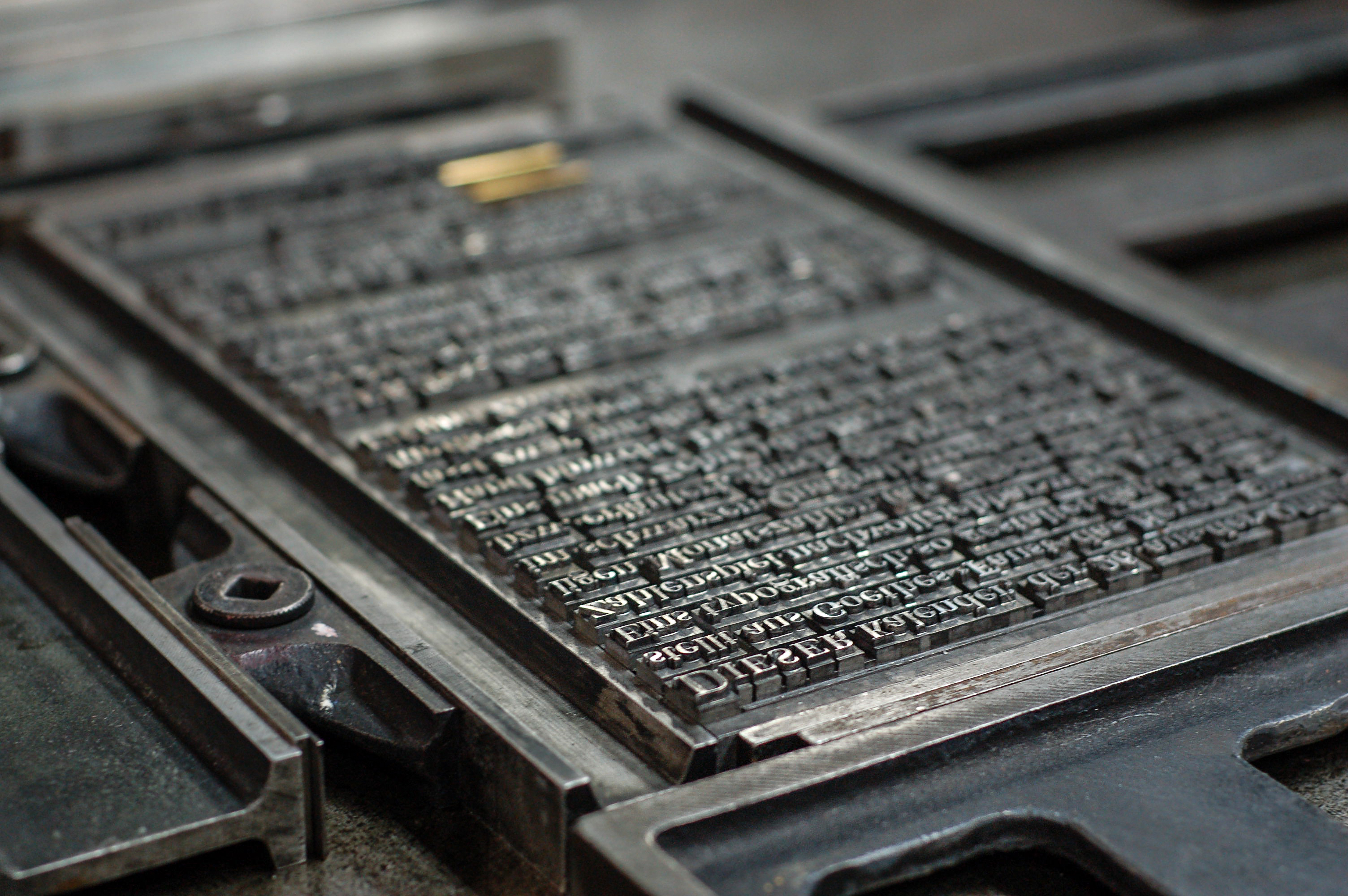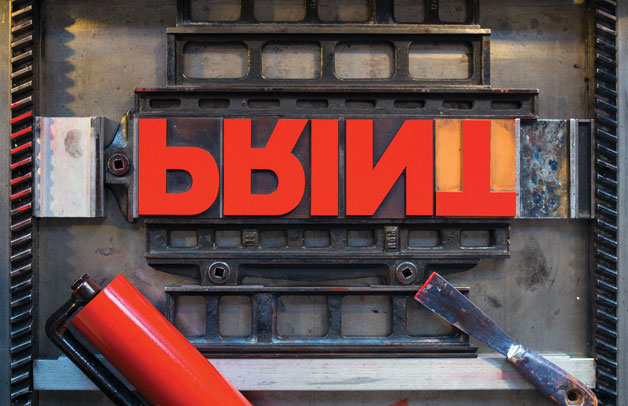
Ich suche ein Foto von Bleisatzlettern
Für einen Call for Content zum Thema «Maschinen» erstellen wir gerade Flyer und Plakate.
Ich hatte den Einfall, dass ein hochauflösendes Foto von einer Bleisatz-Druckmaschine, in die die Druckform mit dem Wort «Maschinen» eingesetzt ist möglicherweise ziemlich gut passen würde. (Das Foto würde ich vielleicht als Hintergrund des Plakats/Flyers benutzen. Wird aber schwarzweiss sein, nicht farbig.)
Ich weiss, dass einige von euch mit Bleisatz zu tun haben und wollte deshalb einfach mal ins Blaue fragen, ob jemand Lust und Zeit hat, ein solches Foto herzustellen und zur Verfügung zu stellen.
Ich weiss nicht, wie aufwendig es ist, so etwas zu fabrizieren mit Einsetzen und alles, verzeiht mir deshalb meine Unwissenheit, falls ich mit meiner Anfrage etwas Unanständiges verlange. :bow:
Ansonsten auch immer gerne Links zu Galerien posten, welche sich auf Fotos von Druckapparaturen, Schrift, Lettern, Typografie spezialisiert haben; würde mich auch sonst interessieren.
Ich schätze, Dir schwebt so was vor wie diese Beispielbilder bei Fotolia, oder? Dort wirst Du nur vermutlich Dein gewünschtes Wort nicht finden, das dürfte zu speziell sein. Falls Du aber doch fündig wirst: die Bildlizenzen bei Fotolia sind in der Regel nicht teuer.
Ansonsten könntest Du auch in eine offene Bleisatzwerkstatt gehen und Dir das Bild selber erarbeiten. Das geht zum Beispiel im Museum der Arbeit in Hamburg, immer montags.
Okay, jetzt hab ich’s verstanden. Das hatte ich gerade eben im Twitter-Stream:
Sowas, nicht war?
wow das gefällt sehr gut. wunderschön. Jap genau sowas schwebt mir vor :D
Ein paar Lettern in den Schließrahmen zu stellen, ist keine große Sache. Wenn du mir eine grobe Skizze machst, in welcher Perspektive und mit wieviel Fleisch drumherum das Bild sein soll, kann ich das machen. Ich fotografiere fast täglich in der Werkstatt. Langzeitbelichtung, kleine Blende, den Rest kannst du dann retuschieren. Welche Art Schrift? Mit oder ohne Serifen? Blei oder Holz?
Das Bild mit der roten Schrift ist natürlich Deko (von jemandem, der auch Zahnstangen einwalzt und Satzformen unsystematisch schließt, also keinem Drucker). Man legt Walze und Spachtel ja nicht auf die Presse. (Pfui, wie der Spachtel aussieht. Die Werkstatt ist wahrscheinlich ein Alptraum.) Ich kann da aber auch irgend etwas hinlegen. Zahnstangen hab ich allerdings nicht.
Hoppla, das war ein Fettnapf. Ich würde mich mal damit rausreden, daß das Foto von einem seiner Workshop-Teilnehmer ist. Spachtel dürfen allerdings trotzdem nicht so aussehen. Da würde ich tobsüchteln, wenn mir damit jemand an einen Farbtopf käme.
(E.S. ist aber tatsächlich kein Drucker.)
Falls noch ein Fettnapf irgendwo für mich steht: Das Wikipedia-Foto zeigt übrigens auch mangelhaften Satz. Ein Initial ohne Randausgleich mit Versalien als Spitzmarke, also etwas ungewöhnliche, aber trotzdem falsche Kapitälchen. Und das Überlegen, also das Ausschließen des freien Raums neben dem Initial, macht man nicht mit Regletten, sondern mit Quadraten und Ausschluß (das sieht man im Druckbild aber nicht, wie es gemacht ist, das ist eigentlich nicht so wichtig). Den Guillemets an »Faust« fehlen die Spatien, die stehen wahrscheinlich zu eng am Wort. Es ist nicht alles Gold, was bleiern glänzt.
Falls noch ein Fettnapf …
Wohl eher ein Farbnapf in diesem Kontext … oder gar eine Tintenfalle, eine heimtückische.  :-D